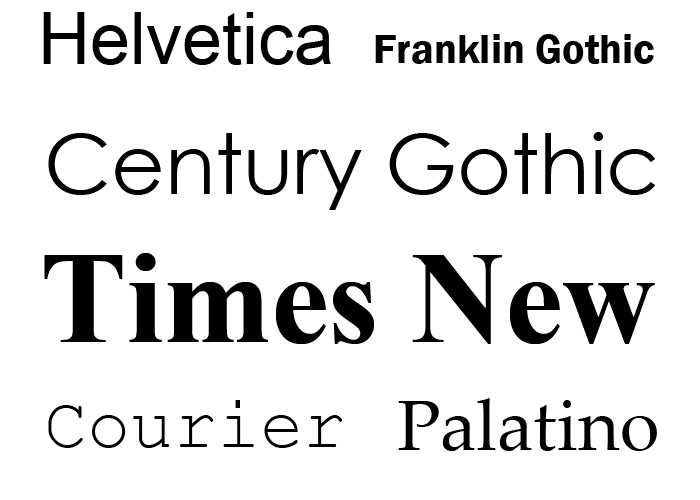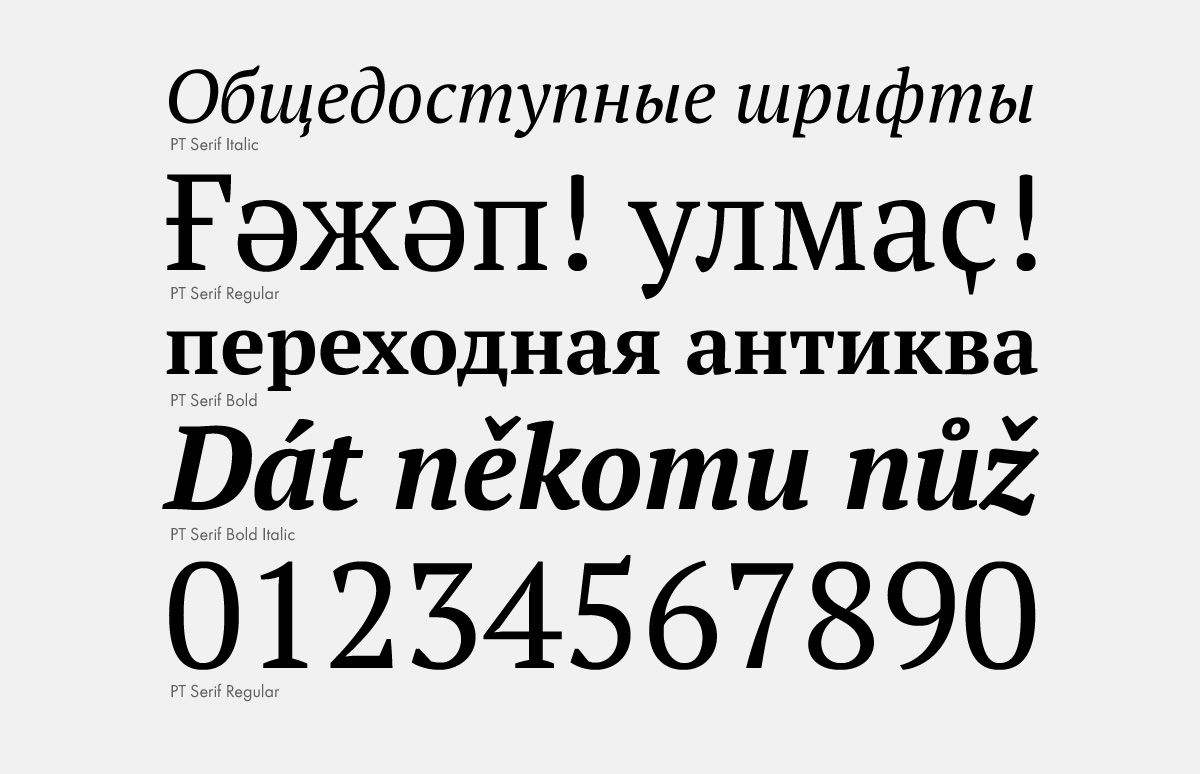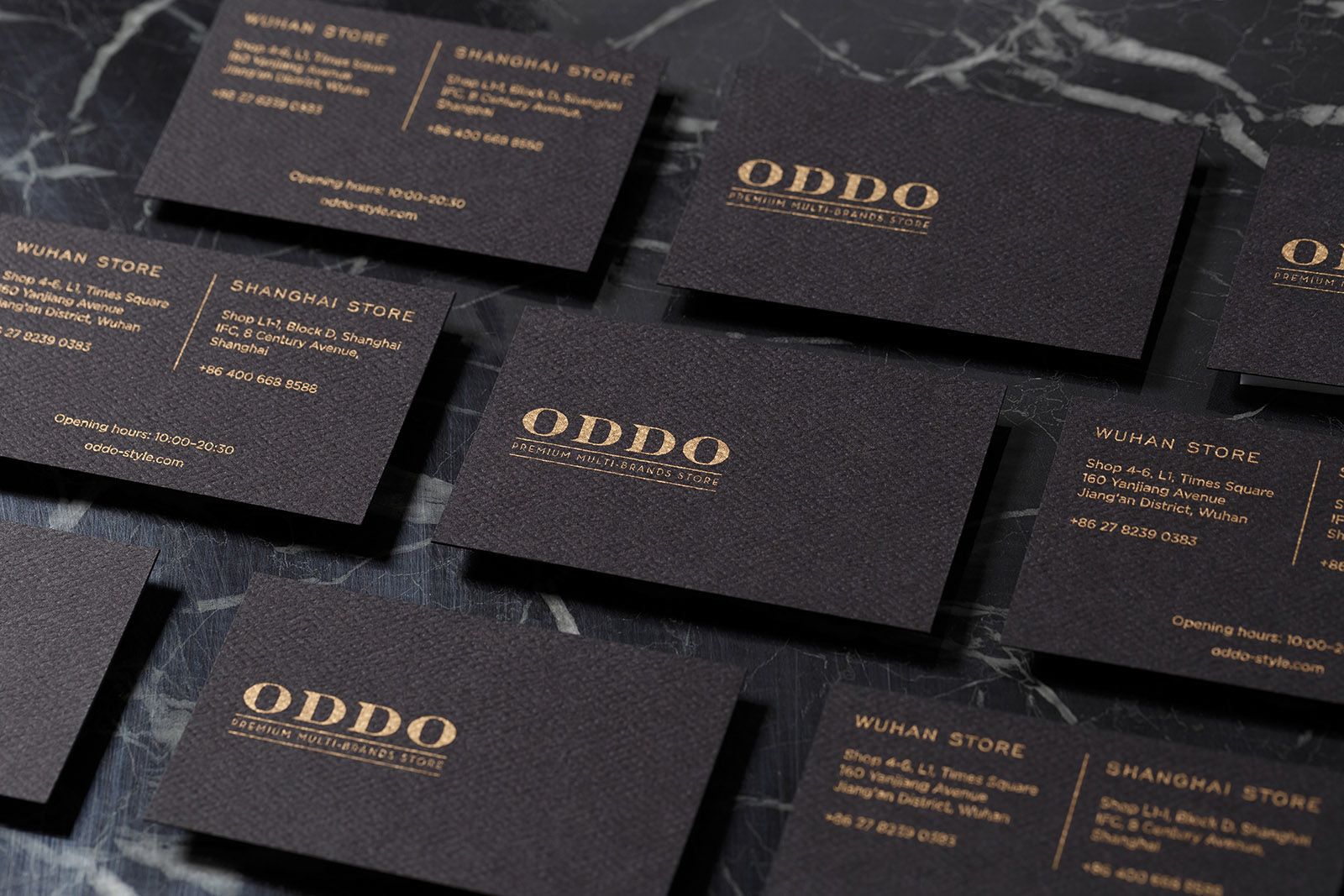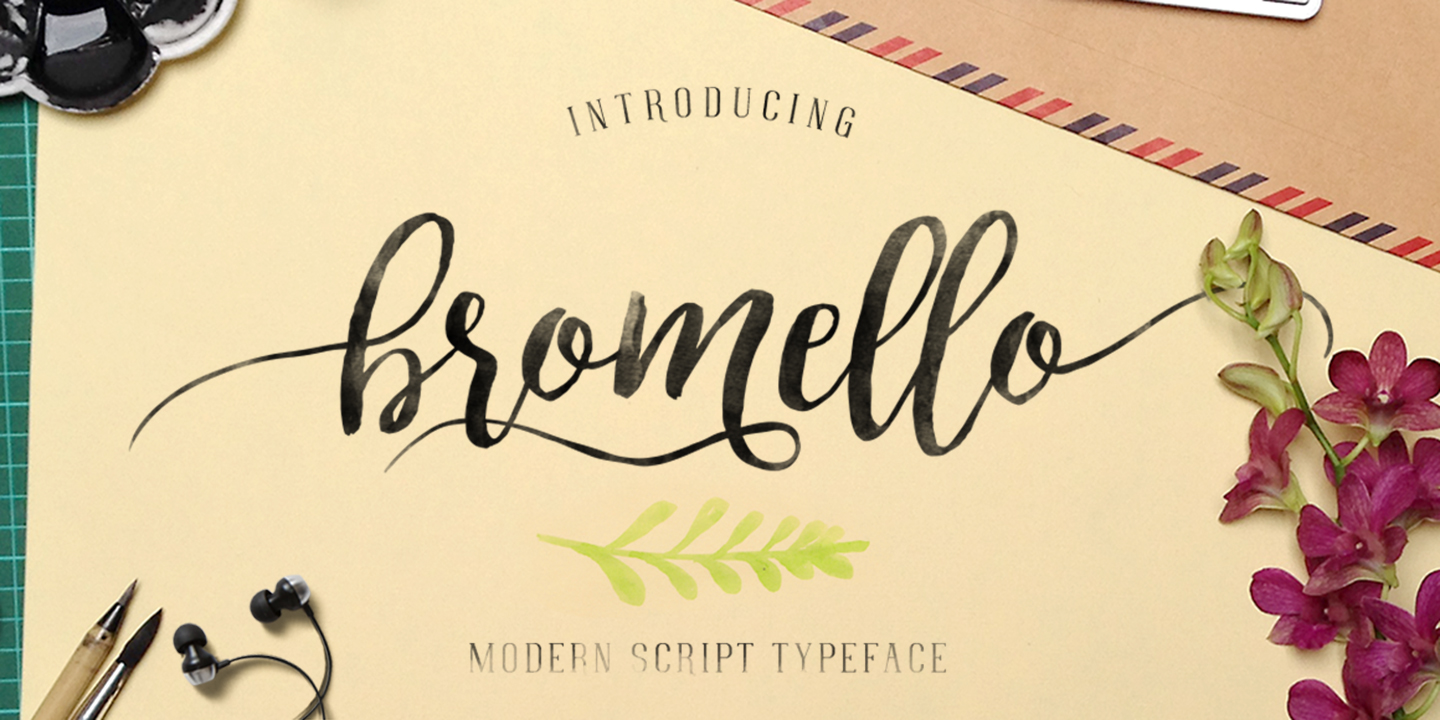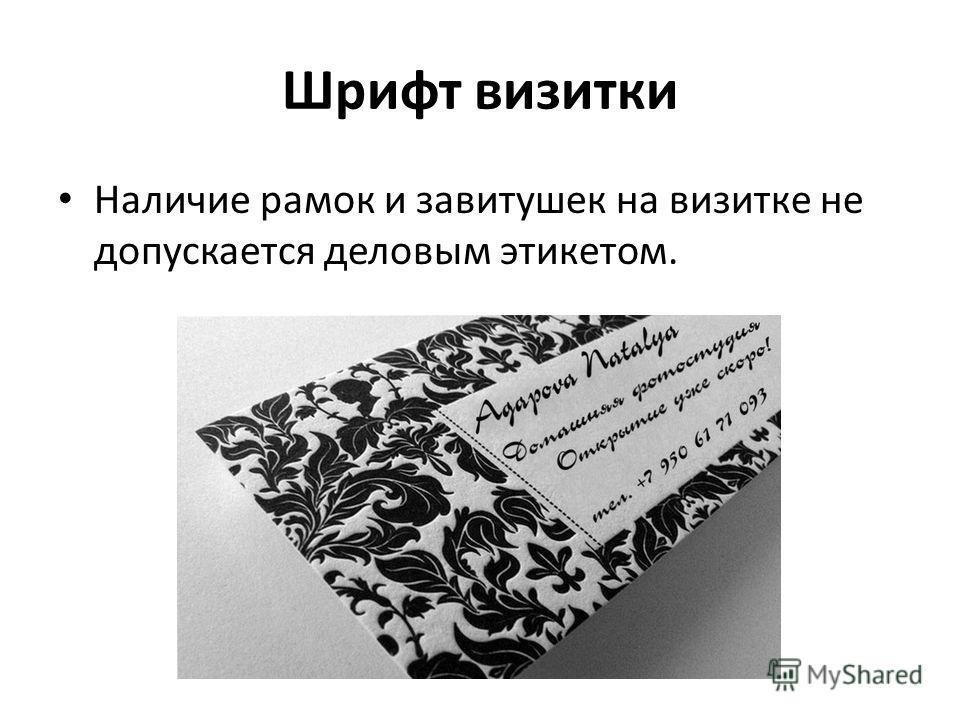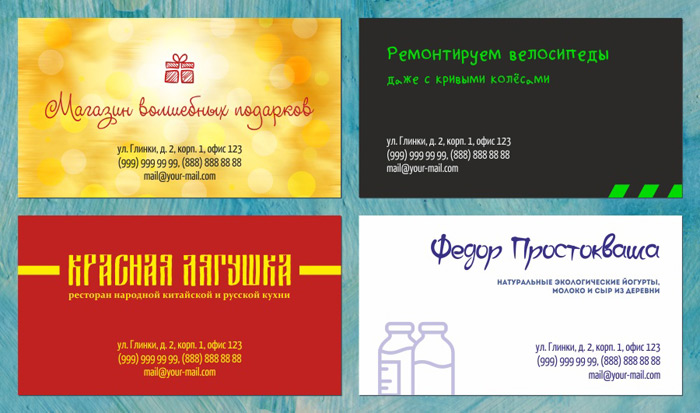
Шрифты русские для визиток: Какие шрифты лучше использовать в дизайне визиток?
Какие шрифты лучше использовать в дизайне визиток?
Меня часто спрашивают, какие шрифты лучше всего использовать в дизайне визиток.
Что-то уже было в статье «7 способов испортить визитку», но есть и еще кое-что.
А не спеть ли мне… эдаким необычным шрифтом, не как у всех?
Визитка делается не с целью удивить людей необычным шрифтом.
Для текста, который должен быть воспринят за доли секунды (имя, фамилия, профессия, контакты) нужно использовать только хорошо читаемые шрифты. Если это смотрится красиво — еще лучше.
В первых двух вариантах использованы шрифты, с которыми знакомы все, — Arial и Times New Roman. Читать их удобно и легко.
В третьем макете «необычные» шрифты сильно затрудняют прочтение текста. Да и выбор их случаен, то есть ничем не обоснован. Какая у этого цель? Видимо, кому-то (директору?) просто так захотелось. Но, вероятно, он не слышал, что дизайн всегда служит решению определенной задачи, а хороший дизайн — незаметен.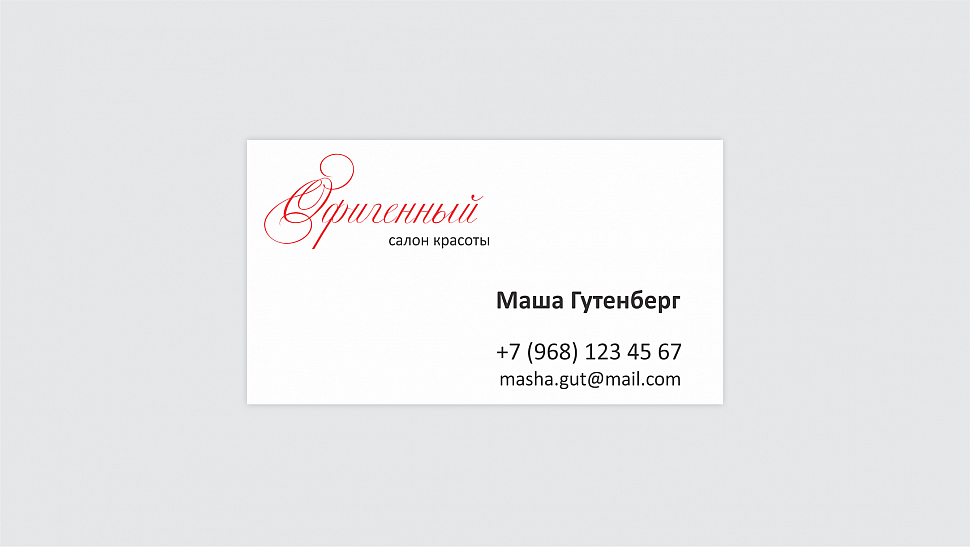
В четвертом макете — симпатичный и ставший модным несколько лет назад шрифт Lobster. На самом деле лучше всего он подходит для меню и рекламы кафе или суши-бара, что доказывает его частое использование именно в таком контексте.
Также он хорош для заголовка, названия или рекламного слогана, но всё меняется, когда его много.
Не набирайте таким шрифтом большое количество текста!
На визитке он может использоваться тоже. Вряд ли это будет карточка адвоката, банкира или чиновника. Если неформальный тон, который задает такой шрифт, — это именно то, что вы хотите передать, используйте его, но помните, что лучше ограничиться одной строкой — например, ФИО:
Получается, «обычные» шрифты лучше?
Это зависит от задачи, но очень часто — да. Если вы делаете строгую визитку, не бойтесь старого Ариала и доброго Таймса, даже если вам кажется, что они выглядят слишком банально и просто, так как они «есть в ворде».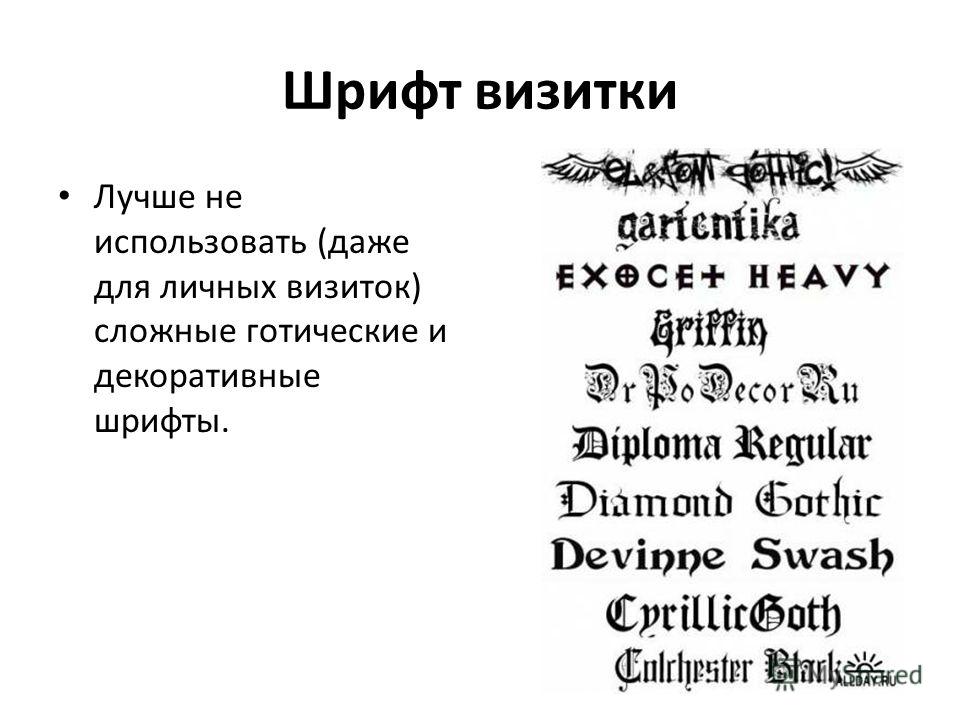
Но ведь есть много красивых шрифтов? Как так, совсем нельзя?
Можно. Но только если это не строгая визитка и если надпись, набранная необычным шрифтом:
— подчеркивает стилистику и тематику;
— поддерживает или усиливает сообщение;
— является (или почти является) логотипом;
— помогает решить задачу.
Если вы хотите взять «необычный» шрифт для своей визитки, но не уверены, выполняет ли он хотя бы одно из условий выше (и нужно ли ему их выполнять), забудьте о нем и посмотрите или вспомните, какие шрифты обычно используются для набора книг.
Такие, которые легко читать, как в двух верхних примерах.
И точно не такие, как два нижних. Они подойдут для других целей.
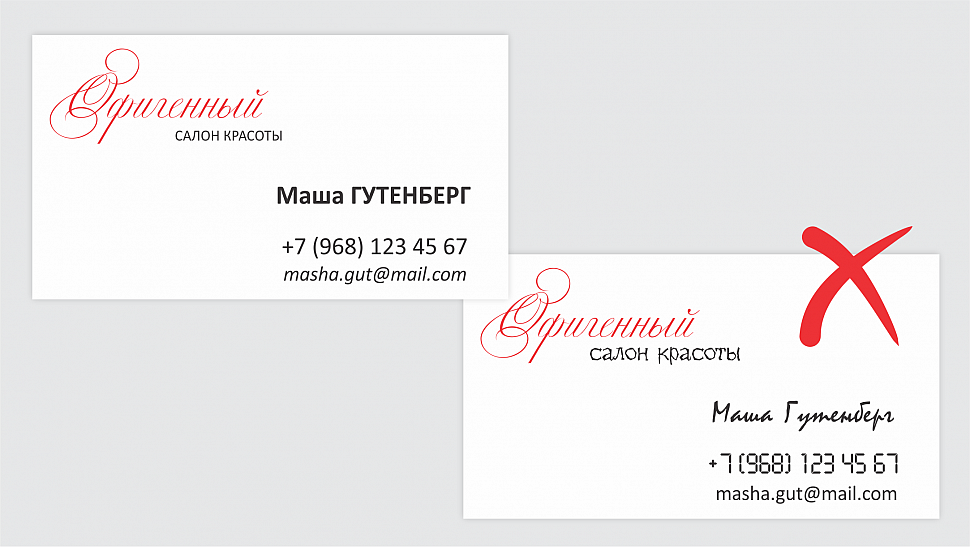
Да, это уже почти конец статьи!
Вот самый простой способ разделить шрифты на несколько групп в виде небольшой блок-схемы (не зря же я получал высшее образование по математической лингвистике). Начнем с вопроса «Подходит ли шрифт для набора большого количества текста?»
Как правильно выбрать шрифт для визитки
Как выбрать шрифт для визитки? Какой размер шрифта считается самым оптимальным? Можно ли использовать разные шрифты на визитной карточке? И вообще, как с помощью шрифта сделать визитку по-настоящему привлекательной? На эти и другие вопросы вы найдете ответы в этой статье.
На данный момент существует огромное количество самых разнообразных шрифтов, а их библиотека постоянно пополняется, предоставляя дизайнерам все больше пространства для творчества и интересных решений. Однако, не стоит забывать о том, что простота — ключ к элегантности! Поэтому, давайте сразу поговорим о том, какие шрифты не стоит использовать в своем дизайне. Плохой шрифт – плохой имидж.
- Comic Sans – слишком детский шрифт. Разве что, вы рекламируете товары или услуги для детей;
- Papyrus – комментарии излишни, не предназначен для деловых документов.
Или в качестве материала для печати вы намерены использовать древнеегипетский папирус? - Arial – потому, что он везде! Вместо него используйте Calibri;
- Courier New – предназначен для написания сценариев. Если вы не хотите, чтобы текст на вашей визитке напоминал титры к голливудскому блокбастеру, не стоит использовать этот шрифт.